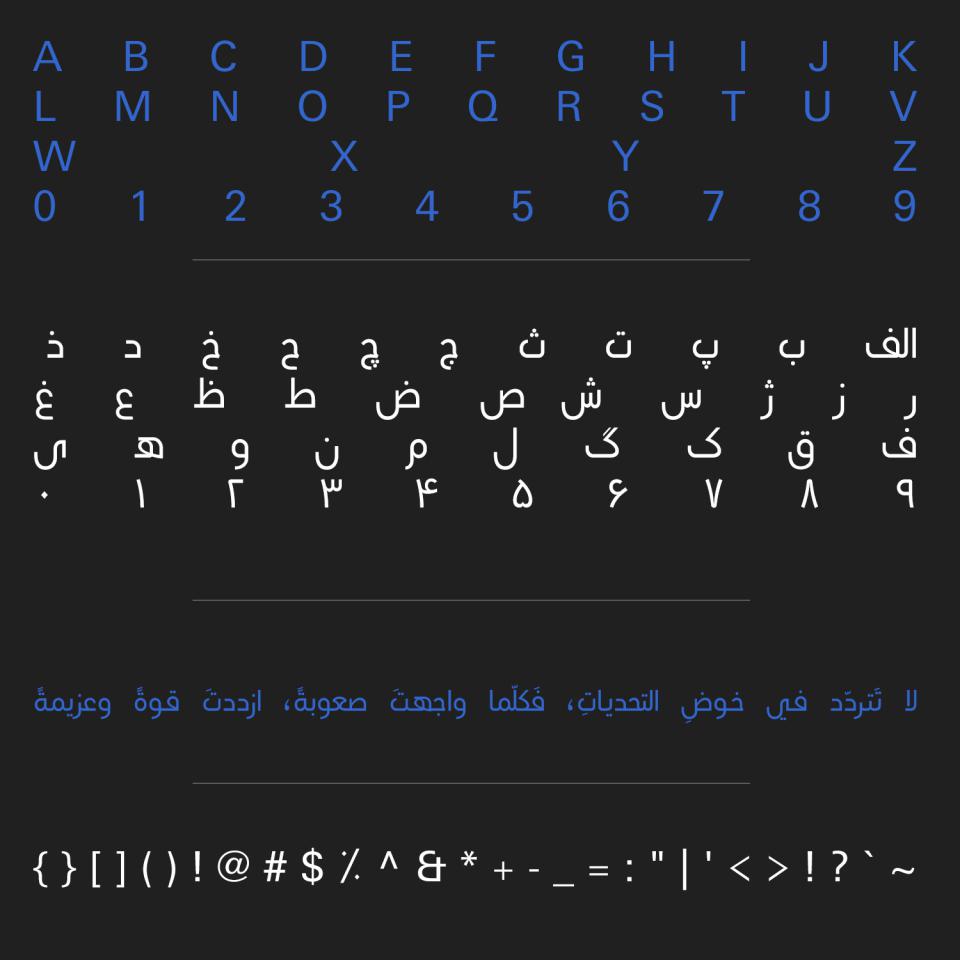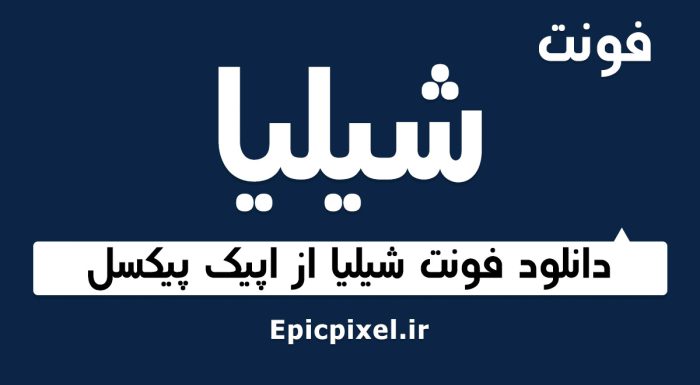
فونت شیلیا، یک انتخاب هوشمندانه برای کسانی است که به دنبال ترکیبی از زیبایی، خوانایی و مدرنیته در نوشته های فارسی خود هستند. این فونت با اصلاح ساختار عربی و تطبیق آن با زبان فارسی، تجربه ای روان و دلنشین از خواندن را ارائه می دهد. یکی از ویژگی های برجسته شیلیا، نرمی و لطافت حروف آن است که به خصوص در متن های طولانی، از خستگی چشم جلوگیری می کند. نقاط دایره ای حروف، یادآور فونت محبوب تاهوما، به شیلیا ظاهری دوستانه و صمیمی می بخشد و آن را برای استفاده در طیف وسیعی از پروژه ها، از طراحی وب سایت و اپلیکیشن گرفته تا تولید محتوای چاپی و دیجیتال، مناسب می سازد.
شاید بتوان گفت شباهت زیاد آن به تاهوما برای برخی یک نقطه ضعف باشد و حس تازگی و نوآوری کمتری داشته باشد، اما همین شباهت باعث می شود برای مخاطبی که به تاهوما عادت کرده، بسیار سریع و راحت قابل پذیرش باشد و به اصطلاح به راحتی با آن ارتباط برقرار کند. این فونت به صورت رایگان در دسترس است و به همین دلیل، گزینه ای ایده آل برای افرادی با بودجه محدود یا پروژه های شخصی به شمار می رود. در واقع، شیلیا با ارائه کیفیتی بالا در کنار رایگان بودن، تعادلی بی نظیر ایجاد کرده است.
اگر به دنبال فونتی هستید که هم زیبا باشد، هم خوانا، هم مدرن و هم رایگان، شیلیا می تواند گزینه ی بسیار خوبی برای شما باشد. این فونت با ویژگی های خاص خود، به نوشته های شما جلوه ای ویژه می بخشد و تجربه کاربری بهتری را برای مخاطبانتان فراهم می کند.